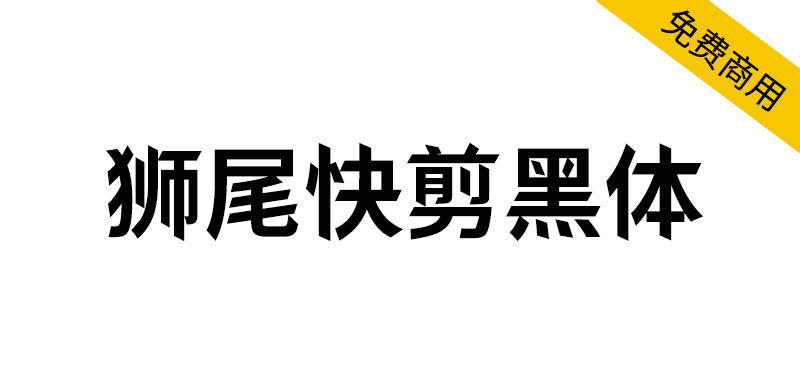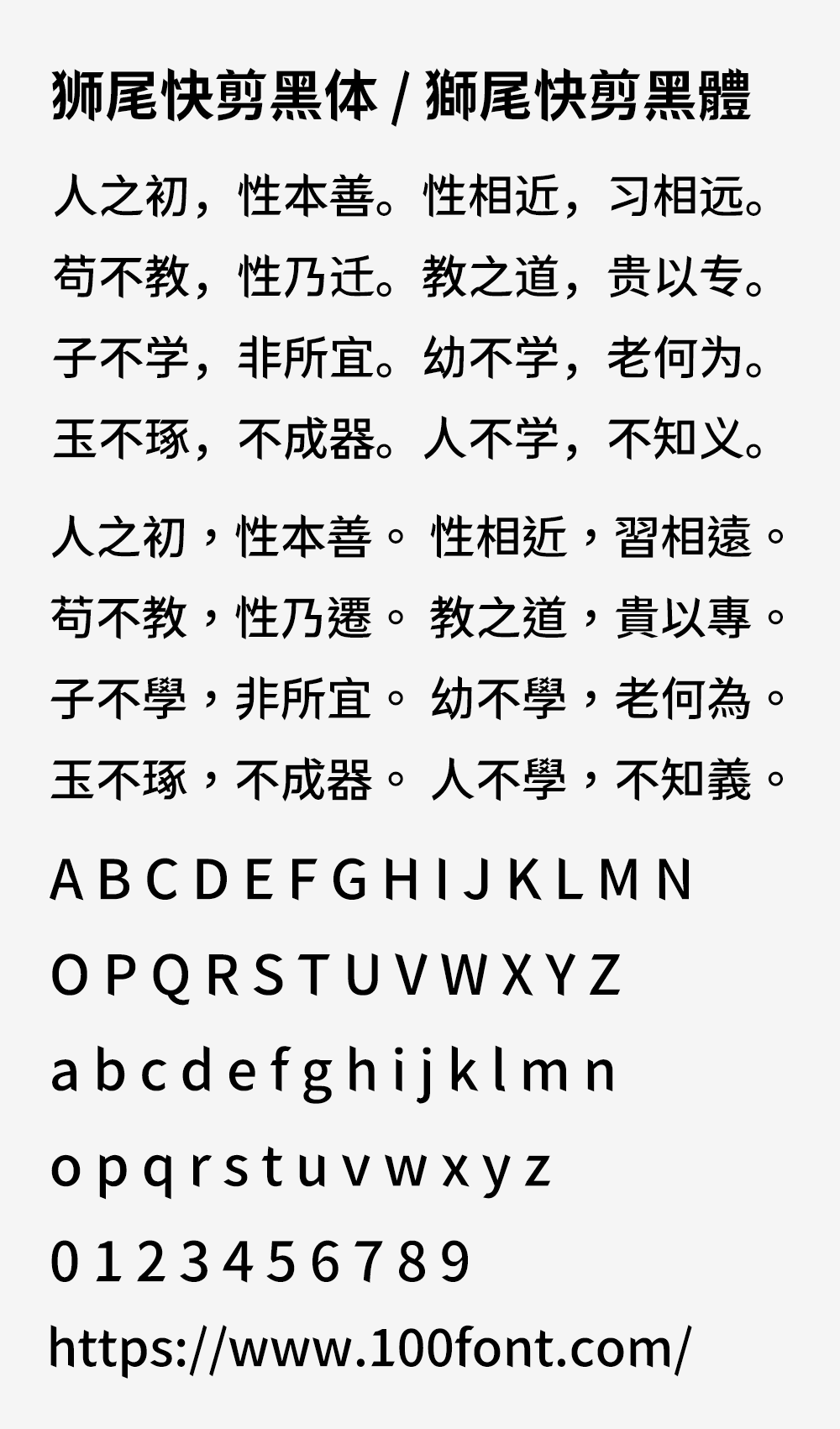
狮尾快剪黑体基于思源黑体的笔触变斜和拔脚改造,更加简明现代化的字体。狮尾快剪黑体的特色是修改原本是水平和垂直的线条为斜线,让字体比较有动感。和思源黑体一样,有7种字重,支持简体中文、繁体中文、韩文与日文,可以免费商用,欢迎大家自由应用、自由优化、自由改作!
狮尾快剪黑体和「狮尾快腿黑体」差别在有没有拔脚,「拔脚」就是会有较少的笔画,例如移除「口」字的左右下角会多出的短线条。有拔脚的字会较圆,但是会造成有些字因直接去掉腿后左右不平衡、左右不对衬的「悬空」问题。改使用「腿」系列字体就不会有这个问题。